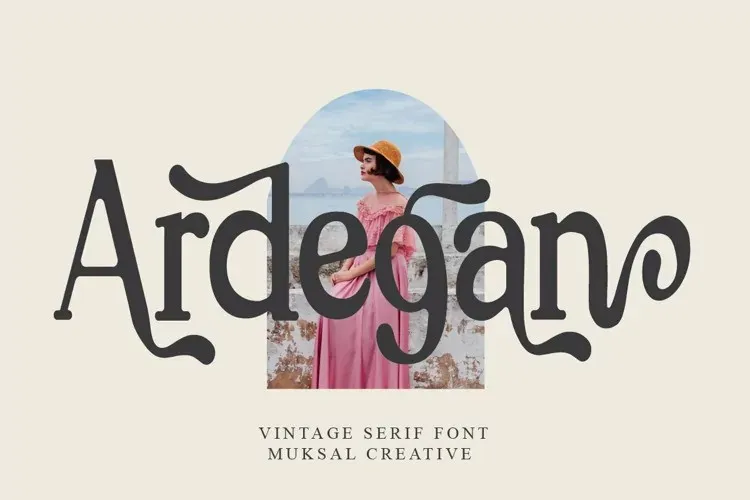
Ardegan Font é uma elegante tipografia serif que traz à tona a beleza natural e delicada dos desenhos humanizados. Com linhas levemente imperfeitas, essa fonte exala um charme único que se destaca em diferentes tipos de design, especialmente quando usado para adicionar um toque sofisticado às suas criações. Suas aplicações podem variar desde convites de casamento ou cartões de felicitação, até logotipos de moda, fotografias e qualquer outro projeto que exija uma aparência sofisticada. O melhor aspecto de Ardegan é sua conveniência em PUA (Unicode Phonetic User Area), que permite que você manipule facilmente todas as formas e curvas do design com apenas alguns cliques. Seja para criar um design minimalista ou algo mais elaborado, Ardegan está aqui para dar vida à cada projeto.